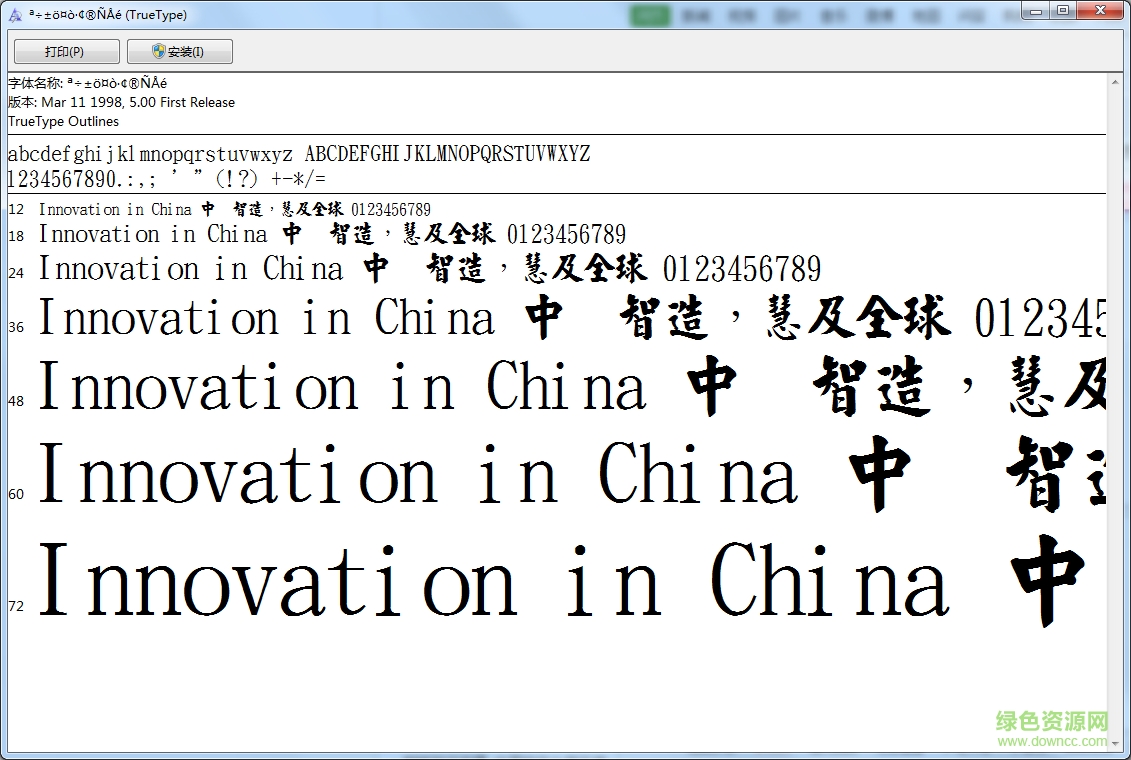
金梅毛楷書體
金梅毛楷書體字體是一款非常好看的金梅字體,支持中文、字母、數(shù)字,字體為楷體,微粗,非常的漂亮,實用性非常的廣,歡迎有需要的朋友到綠色資源網(wǎng)下載使用吧!
金梅毛楷書體字體非常的美觀大方,而且字形非常之工整,使用起來很方便!
這個字體很好看,并且有加粗的效果很醒目,是我想要的效果!